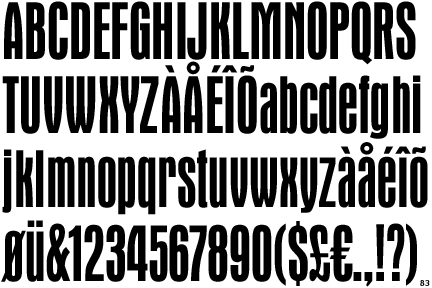
Schmale 1910er-Grotesk
Von der Berliner Börsenzeitung verwendet ab etwa 1918 für Überschriften und Anzeigen.
weitere Beispiele:
die Aurora wurde in der Bitstream-Sammlung mit vielen Corel-Produkten wie Draw mitgeliefert. Hier aus meiner Liste:
Aurora Condensed:
Aurora Bold Condensed:
In Blei hatte diese Schrift verschiedene Namen (u.a. auch Wotan-Grotesk), sie wurde von mehreren Gießereien angeboten.